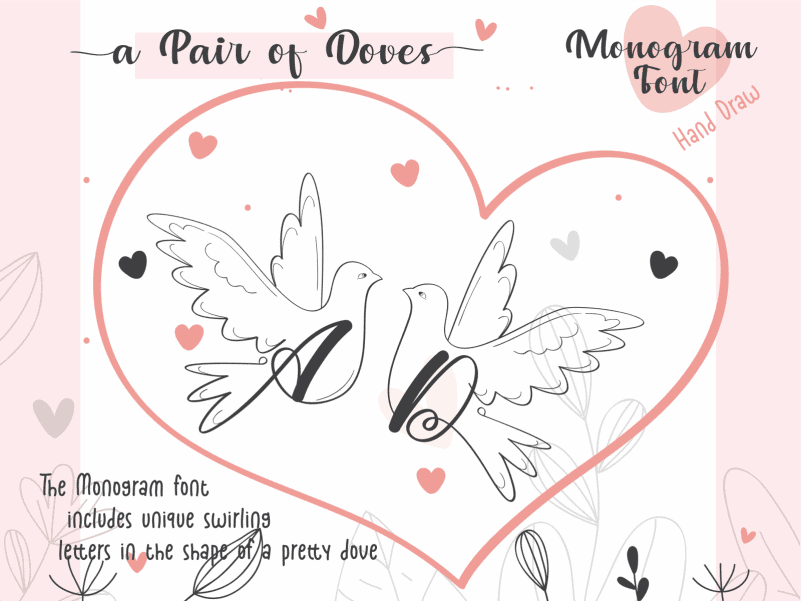
A Pair Of Doves Display Font – Download Grátis
A Pair Of Doves é uma fonte desejável ideal para aqueles que buscam algo único e encantador. Esta elegante tipografia decorativa oferece ornamentos delicados de doves, características que a tornam perfeita para o design de eventos como convites de casamento ou artes decorativas. Sua versatilidade permite incorporá-la em uma variedade de aplicativos, desde postagens interessantes nas redes sociais até arte impactante para sua sala de estar. A Pair Of Doves é um ótimo complemento para aqueles que buscam um toque único e encantador em suas criações. Seu design angelical torna-a uma opção perfeita para os amantes da decoração, criadores de conteúdo digital e designers gráficos que desejam dar um toque especial a qualquer projeto. E não se limite à sua aplicação nas convites de casamento; você também pode usá-la em artes digitais intrigantes ou design de materiais de envio, como cartões de visita, para criar o impacto desejado.